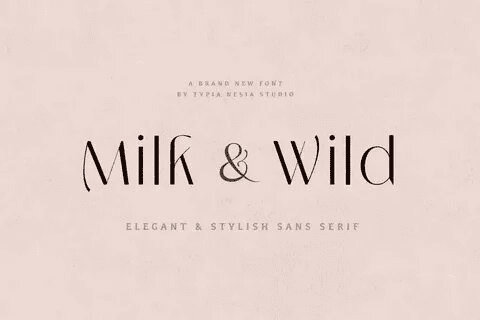
[Fontbundles] Milk and Wild Font
Название: Milk and Wild Font
[Fontbundles] Milk and Wild Font
Milk and Wild - Элегантный гламурный и стильный шрифт Sans Serif - Выразительный современный стильный и красивый шрифт Sans
Элегантный шрифт Milk and Wild Elegant Sans Serif идеально подходит для ваших будущих проектов. Например, роскошный логотип и брендинг, стильный редакционный дизайн, женский журнал, косметический бренд, модный промоушен, брендинг художественной галереи, музея, историко-архитектурного музея, брендинг бутика, дизайн канцелярских принадлежностей, дизайн блога, современный рекламный дизайн, пригласительная открытка, художественная цитата, домашний декор, название книги/обложки, специальные мероприятия и многое другое.